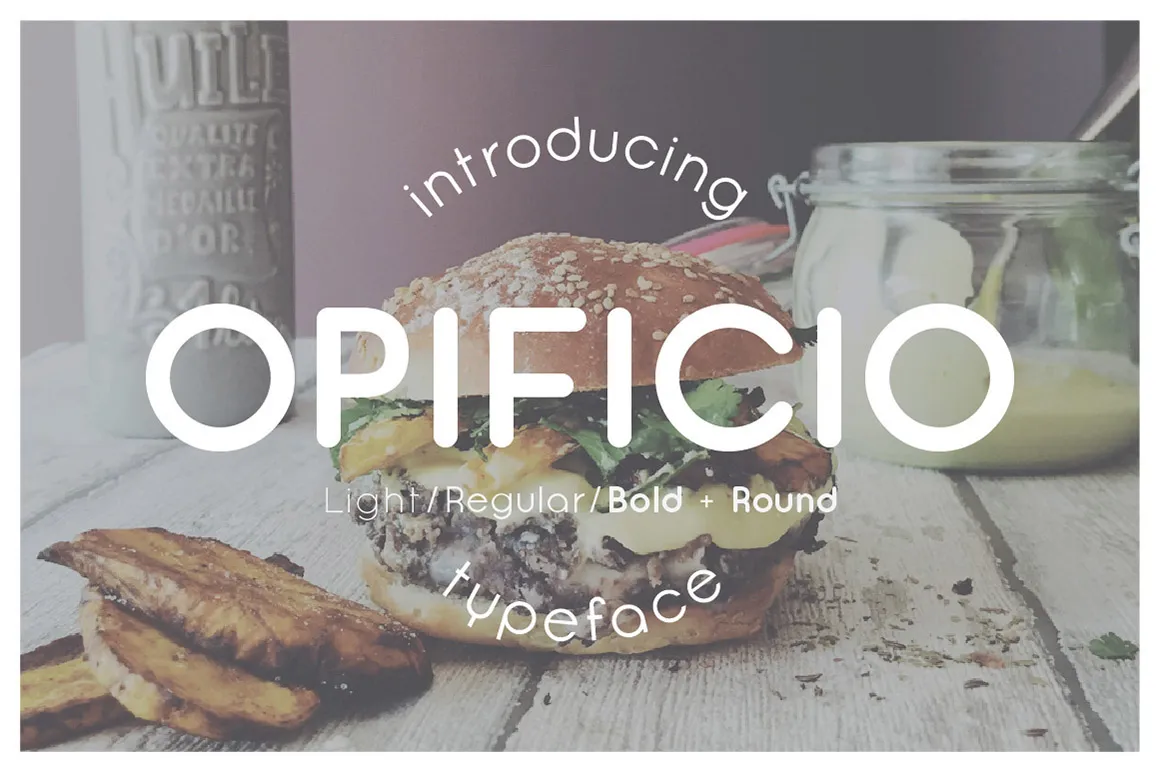
Opificio Font Family
A Opificio Font Family é uma escolha perfeita para qualquer projeto que busque misturar sofisticação com minimalismo, oferecendo uma combinação única de geometria e simplicidade. Desenvolvida em parceria entre o artesão João Malcovitch e a Monofonts, esta família de fontes sans-serif geometrica foi criada para o famoso workshop JM de Prato, conhecido por sua arquitetura geométrica e produtos e móveis minimalistas. Essas características foram incorporadas na designação da Opificio como uma maneira de expressar a personalidade do local, mantendo-se elegante e não invasiva tanto no estilo de display quanto no texto. A Opificio é um sucesso entre os designers digitais e ganhou notoriedade ao ser selecionada para o seção de Design Gráfico pelo Behance, além de ser uma das fontes mais populares criadas pela Monofonts. A família também inclui uma versão arredondada da Opificio (Opificio Rounded), que mantém a estrutura geométrica mas com finalizações arredondadas em vez de quadradas. Esta variação torna o estilo da fonte mais informal e descompromissado, criando um ambiente visual mais descontraído. Ao usar Opificio ou Opificio Rounded na sua próxima produção, você pode capturar a essência do design do workshop JM de Prato enquanto adiciona uma pitada de elegância ao seu projeto. Esta família de fontes é ideal para quem busca transmitir um sentimento autêntico e contemporâneo em qualquer obra visual.
Designer: Monofonts